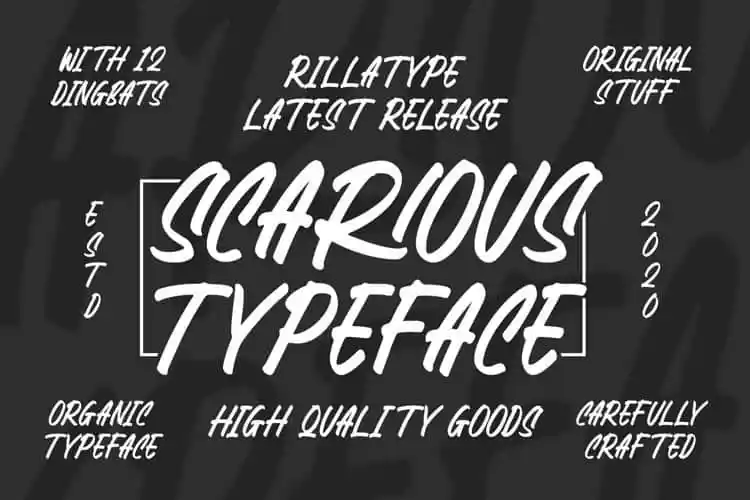
Scarious Brush Font – Download Grátis
Descubra a essência da Scarious Brush Font no designer 99designs. Esta autêntica fonte de traço rústico foi criada com estilo claro e movimento dramático, perfeita para seus próximos projetos criativos como logotipos, cartazes, pacotes de produto, etiquetas e aplicações em tecidos. Com uma aparência moderna e um toque vintage, essa fonte é ideal para tornar qualquer projeto ainda mais atraente e único. Seja para um encarte de revista ou uma camiseta personalizada, Scarious Brush Font traz o resultado que você deseja. Adquira-a agora e dê vida ao seu próximo trabalho!